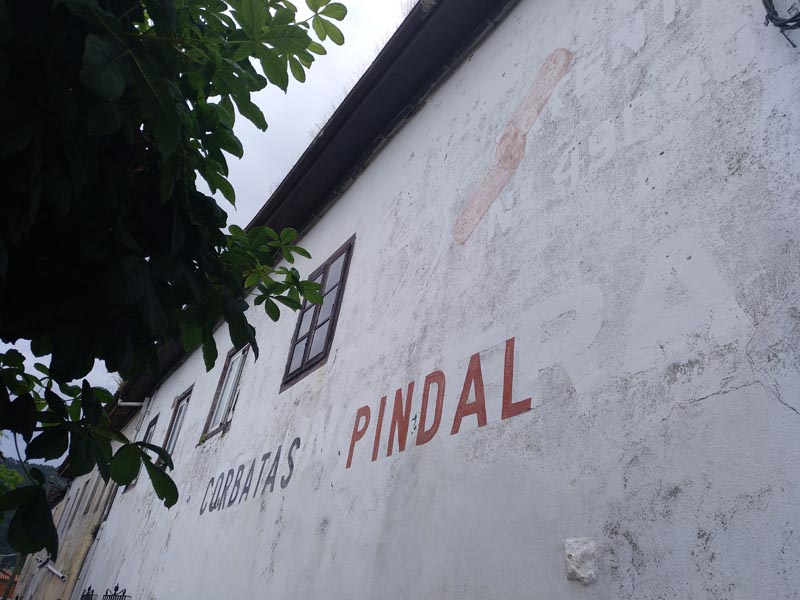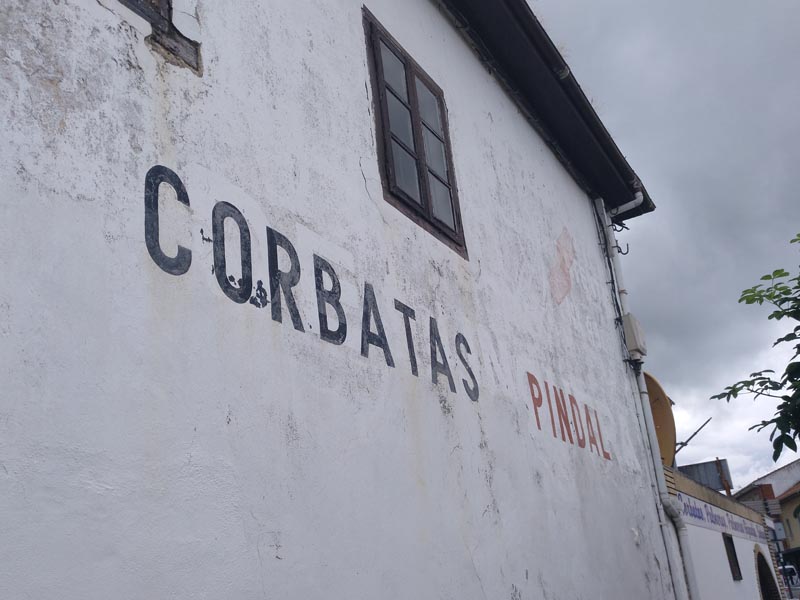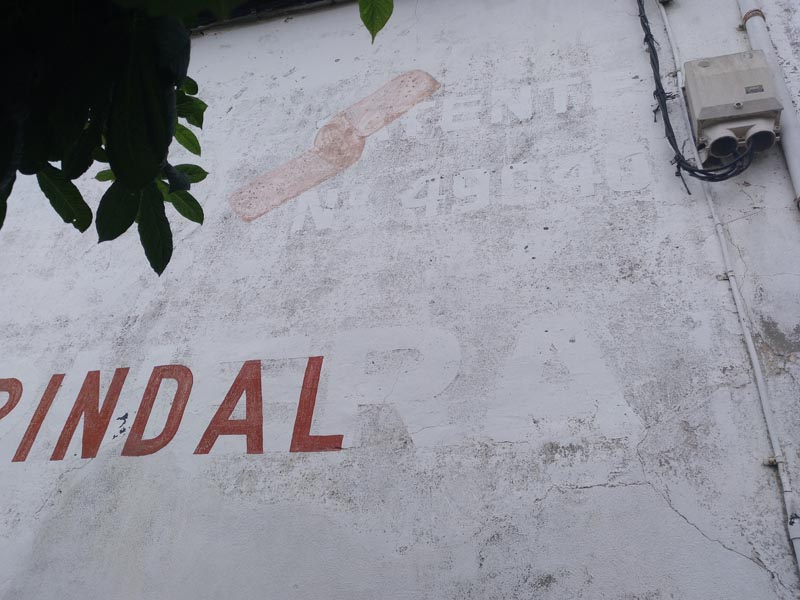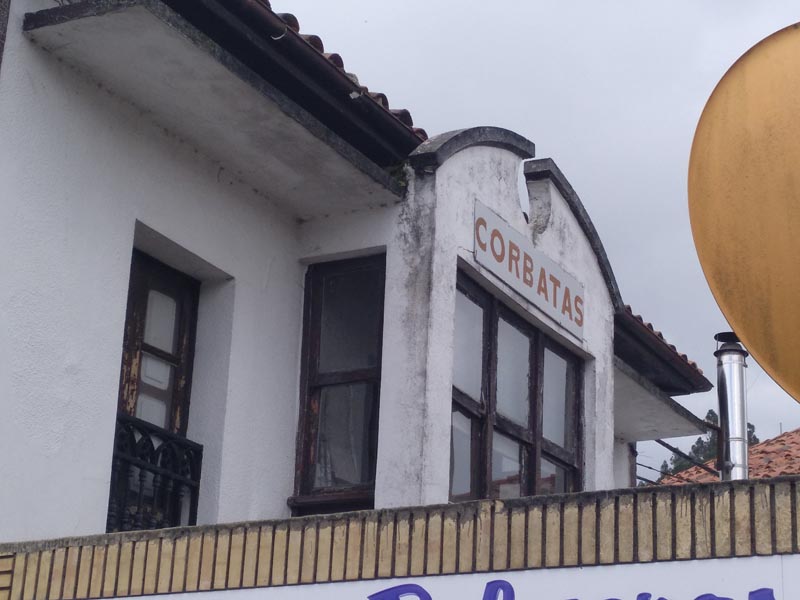
Rótulo original de Corbatas Pindal
Las Corbatas de Unquera son un producto típico de Cantabria hecho con Hojaldre. Y entre los pioneros están Pindal, que en 1981 es adquirido por los Hermanos Junco para extender el negocio denominándose a partir de entonces «Junco Pindal«.  El primer obrador «Pindal 1» hoy cafetería, ubicado junto a la Plaza del Mercado, conserva en una de sus paredes el rótulo original en pintura, sobre otro más viejo.
El rótulo
En la pared se puede leer «Corbatas Pindal» con una tipo de palo seco, en rojo y negro, junto el dibujo de una Corbata.
Corbatas Pindal
Llama la atención que debajo, se dio un revestimiento en blanco y tapó otro rótulo o anuncio. Entre otras cosas se puede leer debajo de Corbatas Pindal: (CORBATAS ¿?) DE UNQUERA, junto a un número: Nº 49040. Si se fija uno bien, arriba de ese número se puede leer: PATENTE, es decir «Patente nº 49040«. Por otro lado, se intuye también la forma de una corbata junto a la que está actualmente pintada, por lo que todo hace indicar que era el anuncio original previo y que dotaba de autenticidad y exclusividad la receta de las Corbatas. Finalmente, sobre la entrada a la cafetería se puede ver el cartel con la palabra «corbatas».